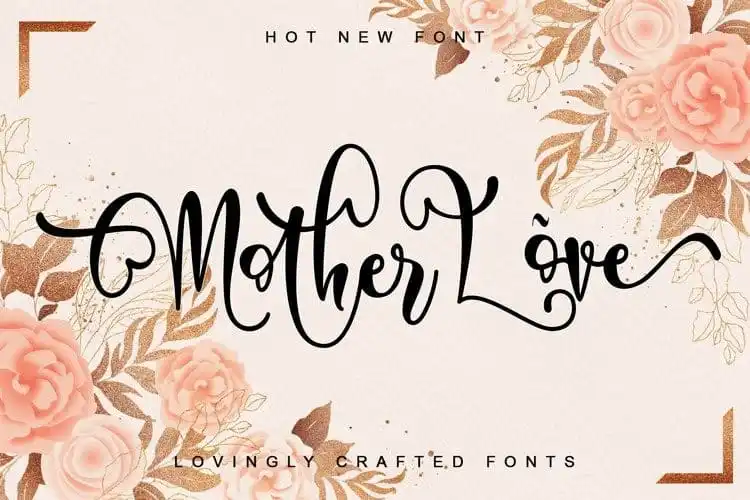
Mother Love Calligraphy Font – Fonte Grátis
Mother Love Calligraphy Font
A Mother Love Calligraphy Font é uma excelente escolha para quem busca uma fonte script elegante e versátil. Criada pelo designer letterara no formato de letra cursiva, esta fonte transmite um ar descontraído e criativo, perfeito para projetos que valorizam a originalidade. Com seus caracteres bem equilibrados e belamente formados, ela se adapta perfeitamente a uma variedade de ideias gráficas, tornando as suas criações verdadeiramente únicas. Seja em um design minimalista ou ornamental, esta fonte vai fazer sua arte soar ainda mais imponente. Além disso, seu PUA (Personal Use Allowed) permite que você desfrute de todos os seus elementos gráficos e ligaturas alternativas sem restrições. Experimente adicionar a Mother Love Calligraphy Font aos seus projetos mais criativos – você certamente será surpreendido pelo resultado incrível que ela pode proporcionar.